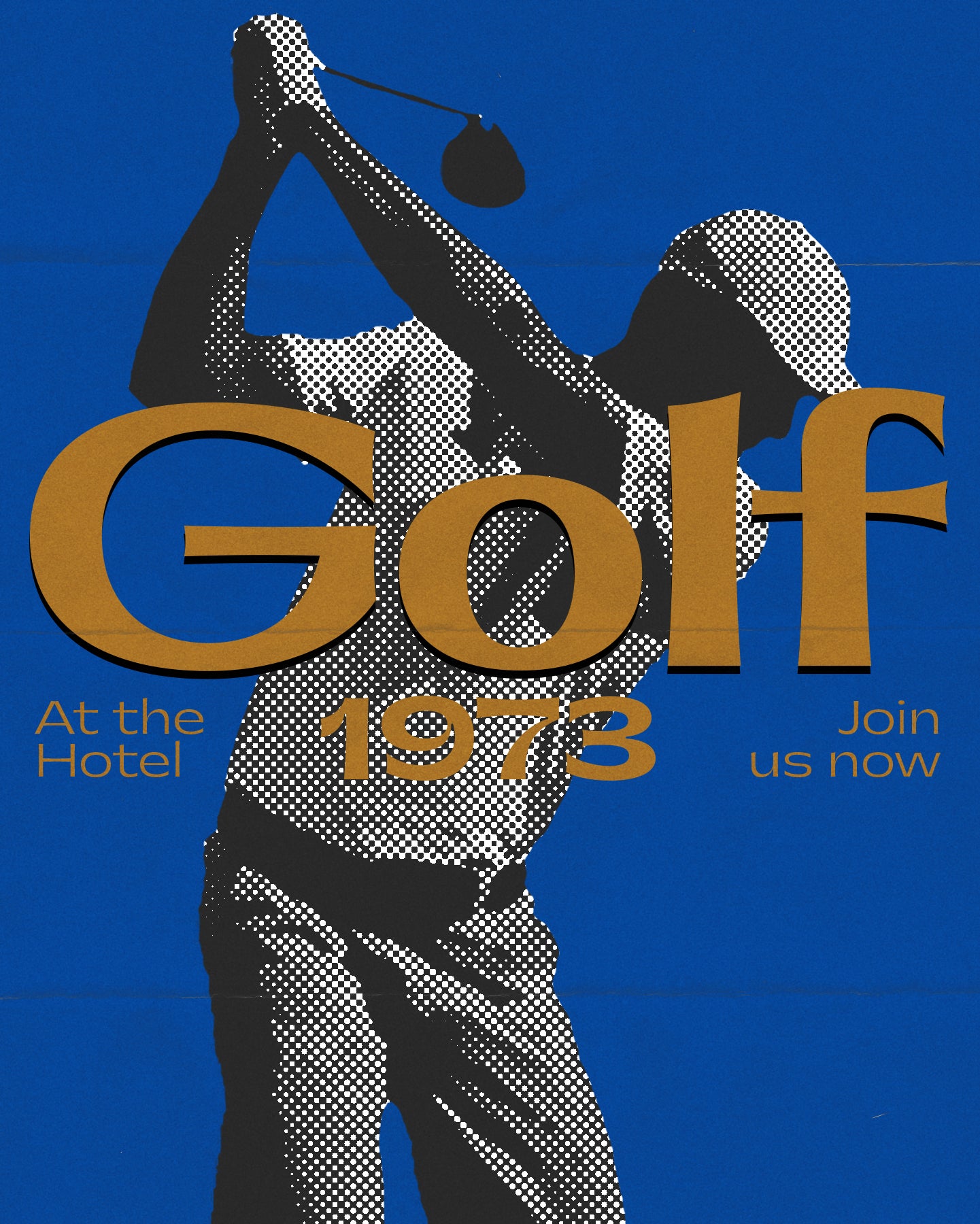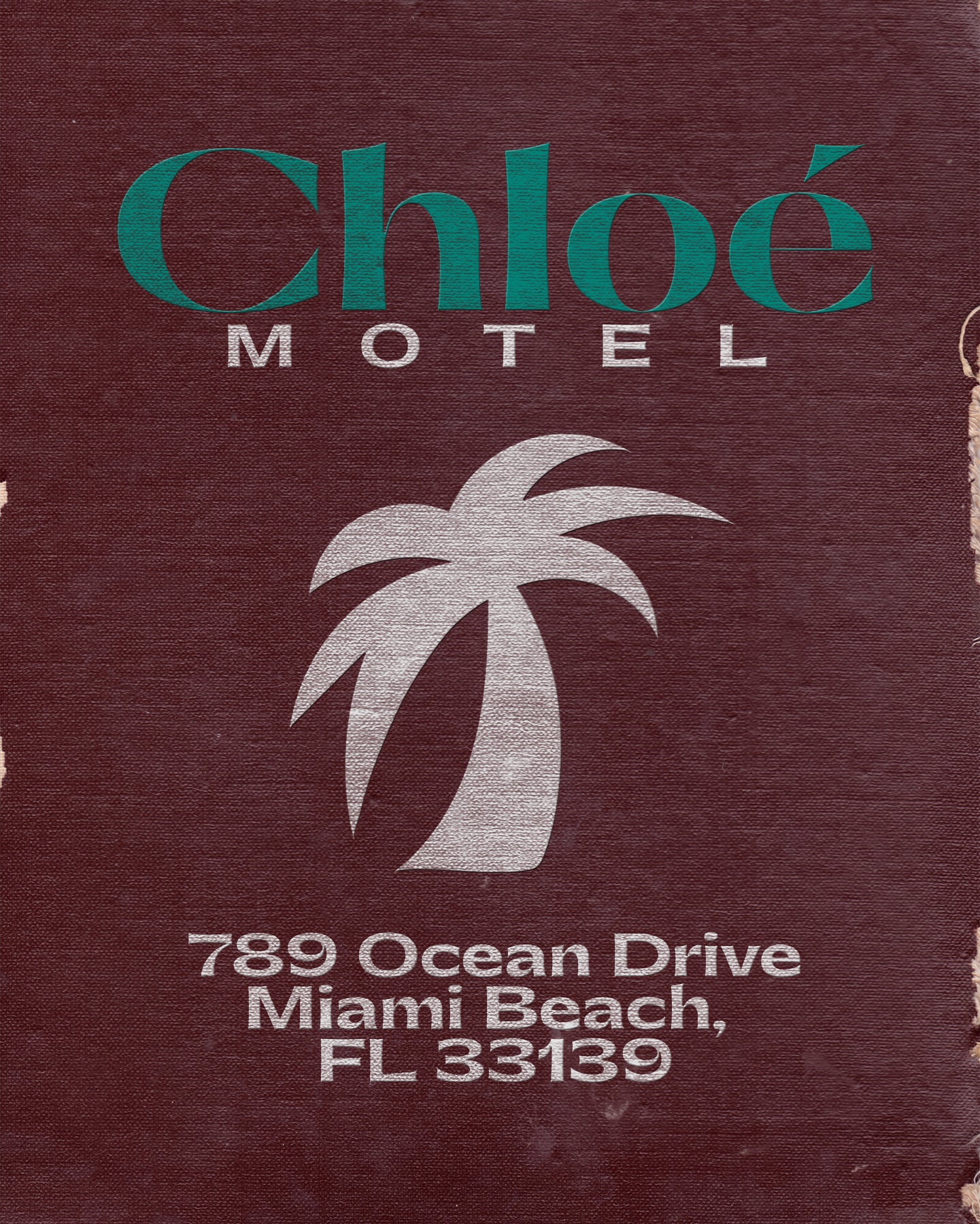
Gatwick Jet
Travel light. Never lightly.
Gatwick Jet
Sharp terminals, and exuberant details.
Gatwick Jet
Gatwick Airport also known as London Gatwick, is a major international airport near Crawley, West Sussex, England, 29.5 miles south of Central London.
Gatwick Jet
The land on which Gatwick Airport stands was first developed as an aerodrome in the late 1920s. The Air Ministry approved commercial flights from the site in 1933, and the first terminal, 'The Beehive', was built in 1935. Scheduled air services from the new terminal began the following year. Major development work at the airport took place during the 1950s. The airport buildings were designed by Yorke Rosenberg Mardall between 1955 and 1988. In the 1960s, British United Airways (BUA) and Dan-Air were two of the largest British independent airlines at Gatwick, with the former establishing itself as the dominant scheduled operator at the airport as well as providing a significant number of the airport's non-scheduled services and the latter becoming its leading provider of inclusive tour charter services.
Gatwick Jet est variable
Gatwick
Jet
Alternate a g
ag
→
ag
Case sensitive forms
{[(OH-@11:11!)]}
Standard ligatures
fi ff ffi fl ffl
Old style figures
0123456789
Voyagez léger. Jamais à la légère.
Gatwick est une police à larges incisions qui allie une attitude funky à un esprit raffiné, s'harmonisant aussi bien avec les esthétiques vintage que contemporaines de manière unique et mémorable. Contrairement à de nombreuses polices de son genre qui misent sur des proportions uniformes et une épaisseur constante pour conserver un ton neutre, Gatwick se distingue par ses fûts effilés, ses terminaisons nettes et ses détails exubérants. Ce style distinctif lui confère un caractère exotique et extravagant qui attire immédiatement le regard.
Avec la sortie de la version 2.0, Gatwick élargit sa polyvalence en introduisant deux nouvelles familles à contraste élevé. Ces ajouts sont parfaits pour créer des titres et des sous-titres élégants, ajoutant une touche de sophistication supplémentaire à tout projet. Conçu pour propulser votre travail créatif vers des destinations nouvelles et inattendues, Gatwick offre la fiabilité et le confort d'une expérience haut de gamme, tout en garantissant que vos créations laisseront une impression durable.